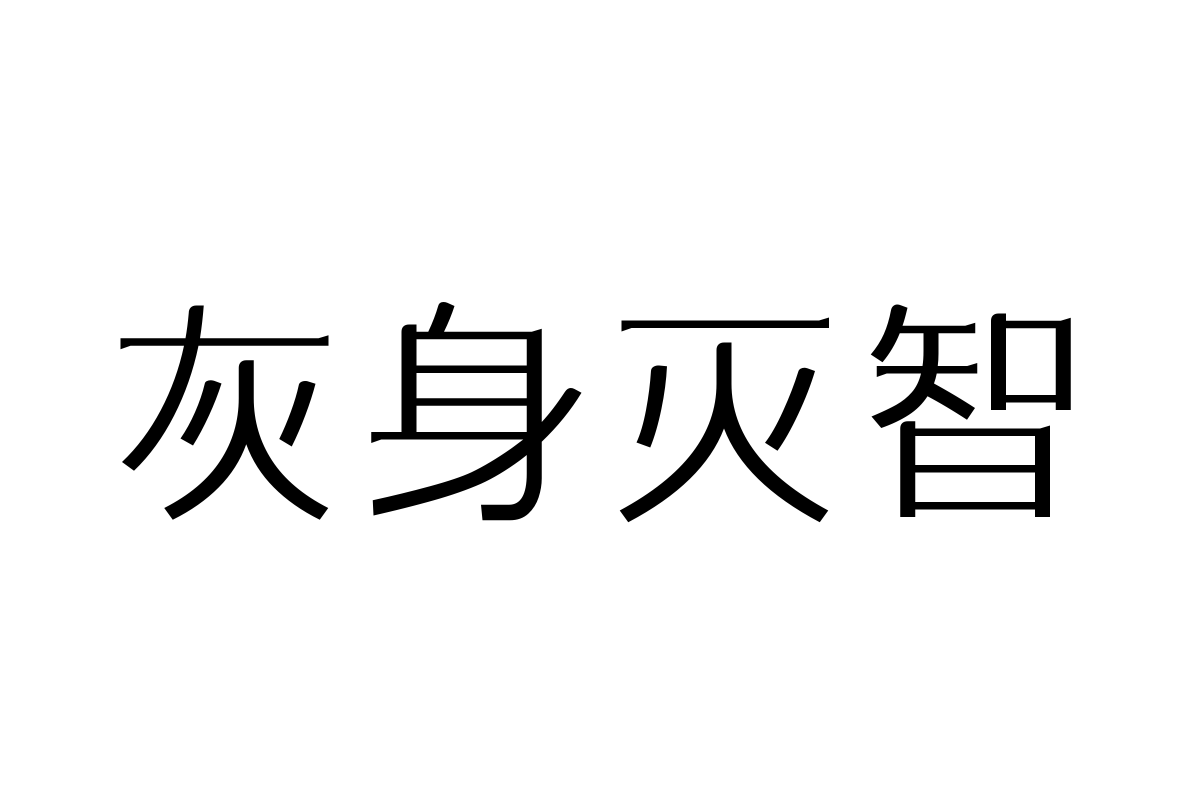
三极素纤简体字体是一款简洁、现代的中文字体,具有清晰的字形和优雅的笔画。它的设计灵感来自于传统的书法艺术,但又融入了现代审美元素,使得这款字体既保留了传统文化的韵味,又符合现代人的审美习惯。
三极素纤简体字体的特点如下:
1. 字形清晰:字体笔画流畅,字形结构紧凑,易于阅读和识别。
2. 美观大方:字体线条流畅,造型优美,给人以视觉上的享受。
3. 适合多种场景:无论是用于书籍、报纸、杂志还是网页设计,三极素纤简体字体都能展现出良好的视觉效果。
4. 支持多种字重:提供多种字重选择,满足不同场合的需求。
总之,三极素纤简体字体是一款适合现代设计需求的中文字体,无论是在印刷品还是电子媒体上都能展现出良好的效果。